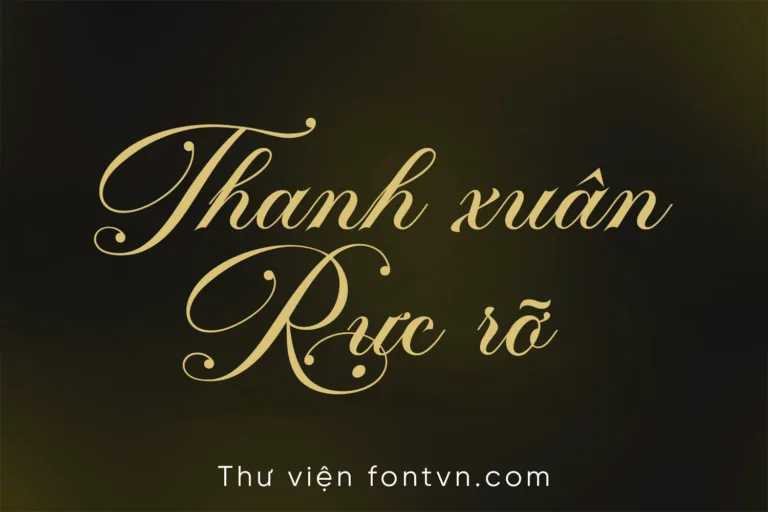
DVN Sakura Việt hóa – Font chữ uốn lượn tinh tế dành cho thiệp cưới, mỹ phẩm
Font chữ DVN Sakura là một kiểu serif tinh tế, mang phong cách cổ điển pha lẫn hiện đại. Điểm nhấn chính của font nằm ở những đường nét cong mềm mại, uốn lượn đặc trưng trên các ký tự chữ hoa, tạo cảm giác thanh thoát và độc đáo. Các ký tự chữ thường lại đơn giản và dễ đọc, giúp cân bằng tổng thể giữa tính nghệ thuật và tính ứng dụng. Bộ glyph phong phú của DVN Sakura cung cấp nhiều lựa chọn cho việc thiết kế sáng tạo, đặc biệt phù hợp trong việc sử dụng cho logo, tiêu đề hay các ấn phẩm in ấn đòi hỏi sự nổi bật. Bên cạnh đó, font còn có hệ thống dấu câu và số học đầy đủ, hỗ trợ tốt cho nhiều nhu cầu thiết kế đa dạng. DVN Sakura đem đến cảm giác sang trọng nhưng không kém phần mềm mại, làm nổi bật những dự án thiết kế yêu cầu sự tỉ mỉ và tinh tế.
Font có hỗ trợ Ligature và Glyphs giúp bạn tạo ra hiệu ứng chữ hoa lá, xem hướng dẫn dùng Ligature và Glyphs tại đây